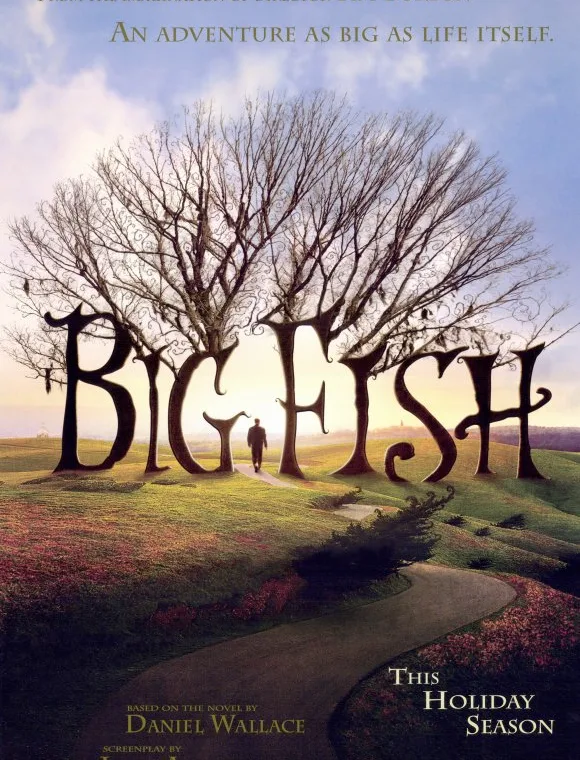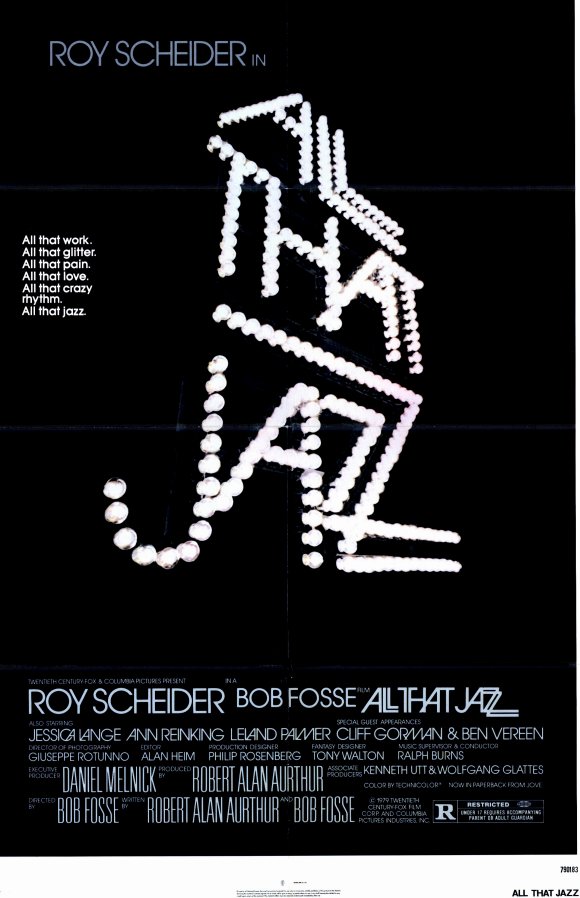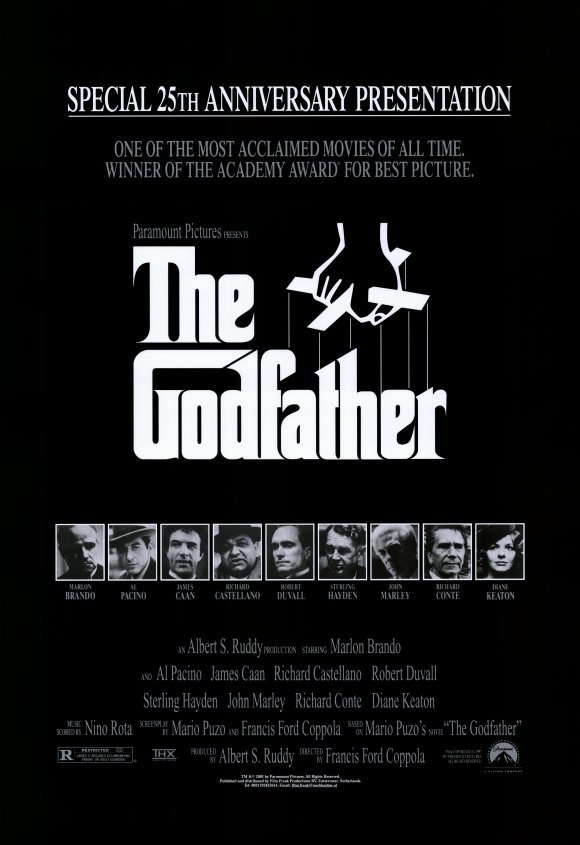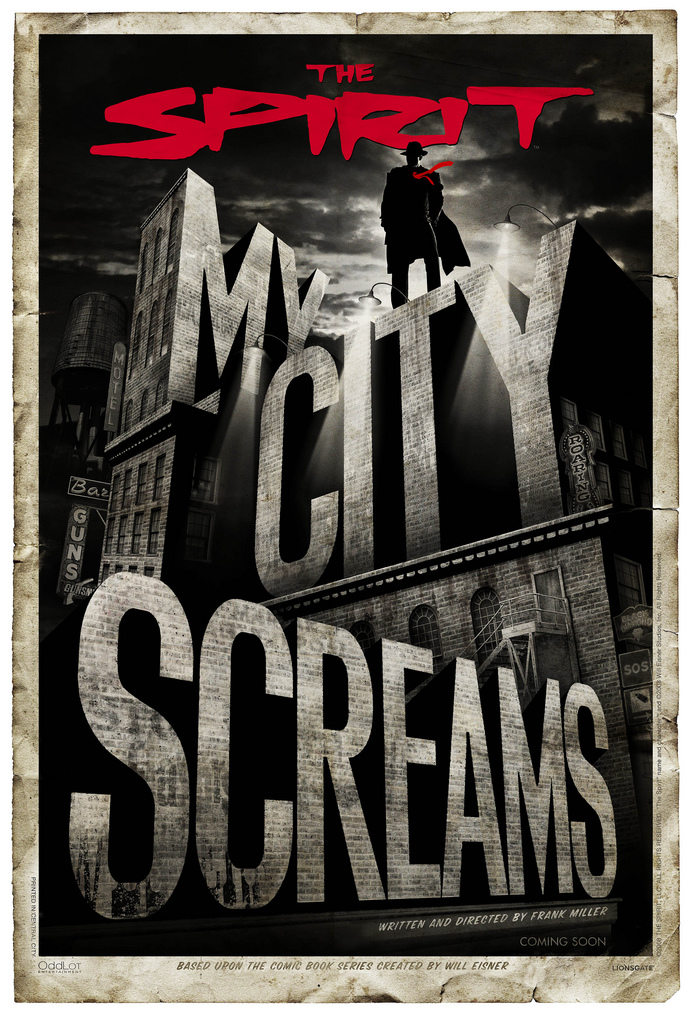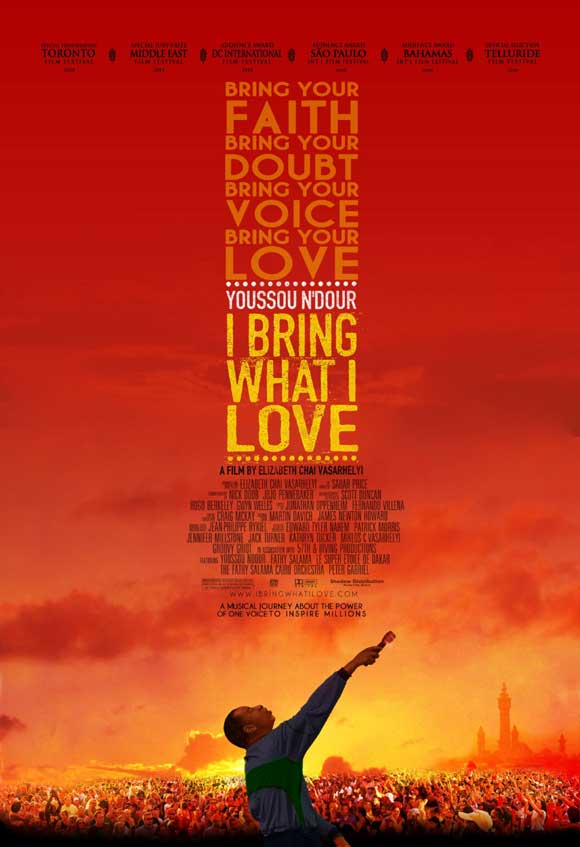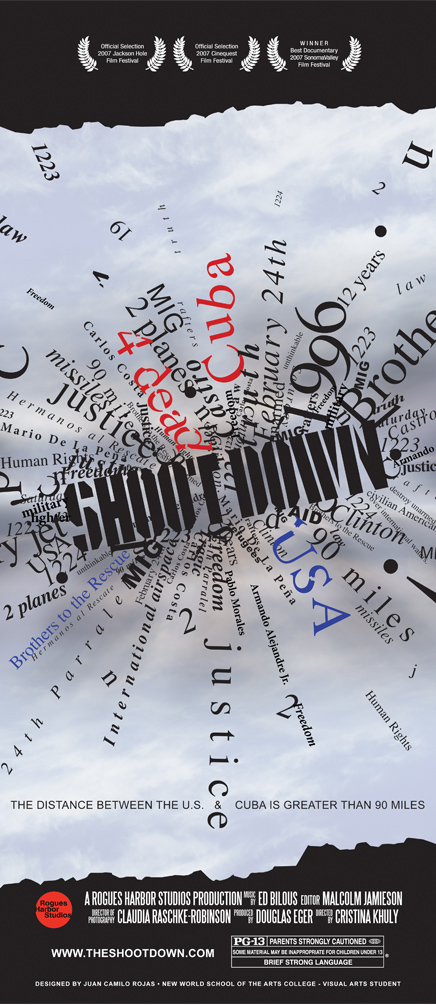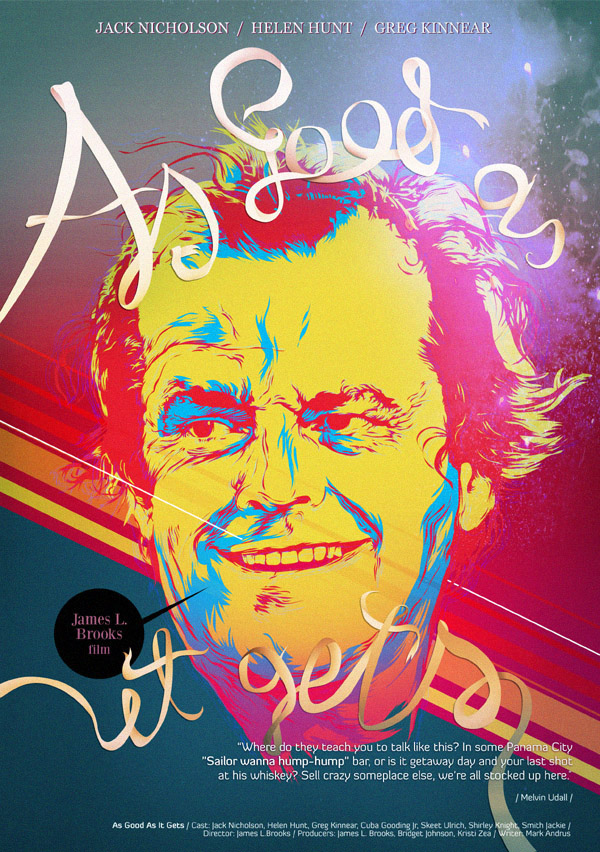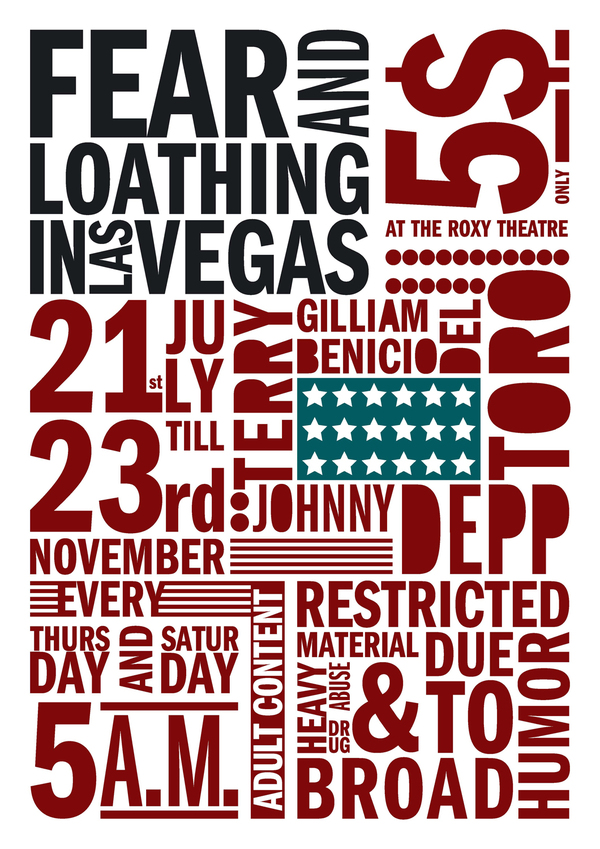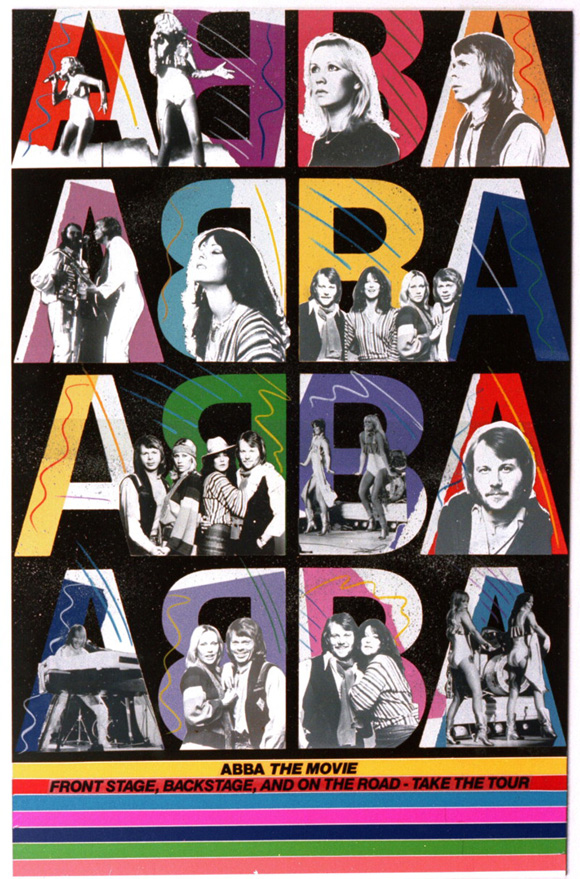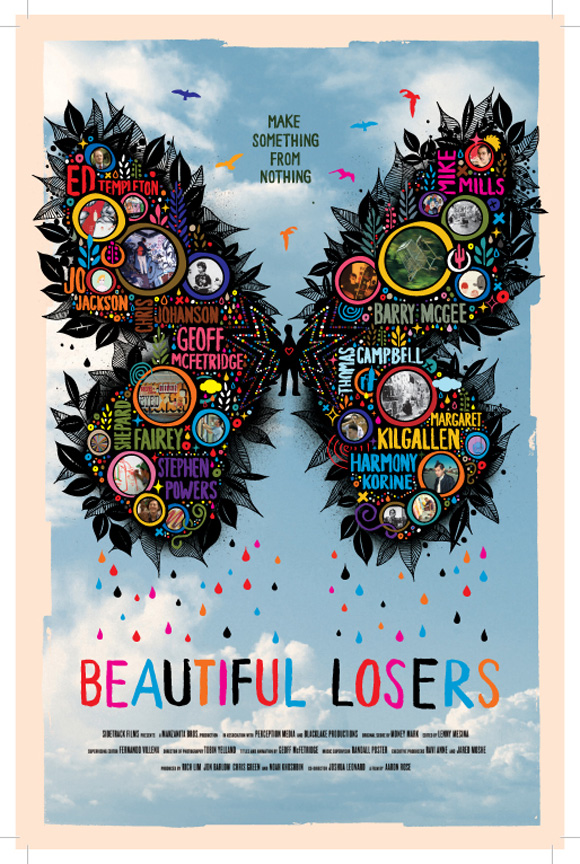
19 exemplos criativos do uso da tipografia em capas de filmes
Vejam que não é só necessário criar uma capa de filme com montagens de fotografias e ilustrações, o bom uso da tipografia e a forma que ela é posicionada em um projeto as vezes nem precisamos de nos preocupar com as imagens.
Separei alguns exemplos bem criativos para vocês terem uma ideia que as vezes uma palavra vale mais do que mil imagens.